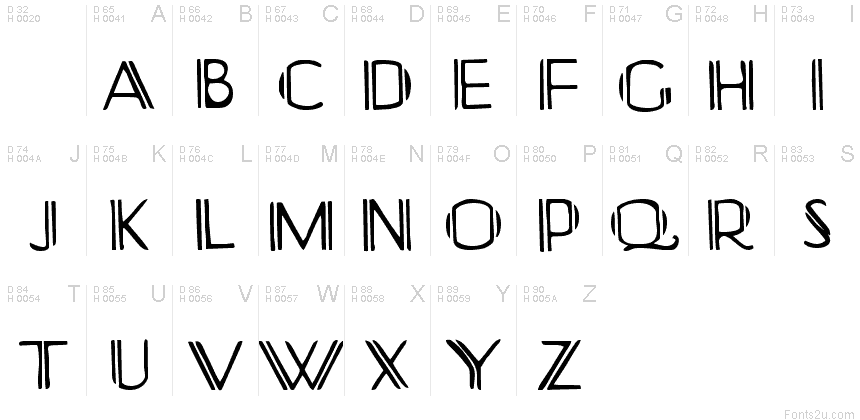
Yonkerismo, bezpłatny retro font typu display autorstwa Rev. Josh Wilhelma, czerpie inspirację z estetyki szyldów z połowy XX wieku. Litery zdają się być zbudowane z dynamicznych, zwężających się linii, które rozdzielają się i łączą w sobie, nadając krojowi lekki, jazzujący charakter, daleki od topornego wyglądu typowych plakatów.
Sprawdza się wszędzie tam, gdzie potrzebny jest szczypta nostalgii – na ulotkach w stylu lounge, w brandingu nawiązującym do amerykańskich barów, na okładkach płyt, planszach tytułowych czy monogramach. Jako darmowy font, Yonkerismo sprawdza się zwłaszcza przy krótkich nazwach i nagłówkach, ponieważ wąskie, rozgałęzione kształty sprawiają, że nawet kilka liter nabiera artystycznego, odręcznego wyrazu.